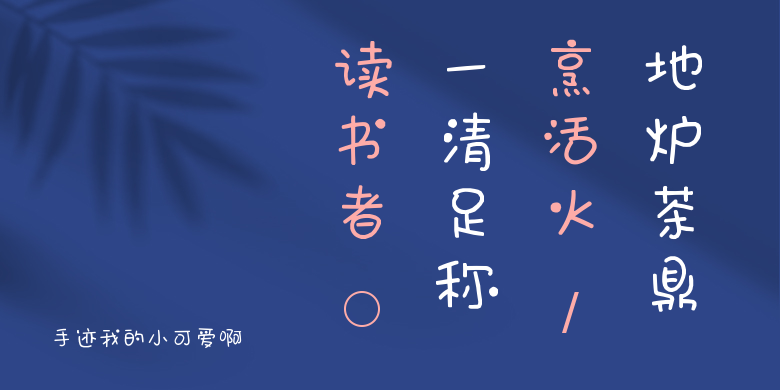
手迹我的小可爱啊
手迹我的小可爱啊,这款字体结构工整、笔画清晰,兼顾美观与易读性,适用于标题、正文、海报、包装、LOGO 等多种场景。字形优雅稳定,风格百搭耐看,适配日常排版与创意设计,让文字呈现更舒适、更具质感。手迹我的小可爱啊一笔一画,皆是细节,以均衡的比例、流畅的线条打造舒适视觉体验,字形端正大气,风格简约现代。无论是商业设计、品牌宣传还是日常排版,都能轻松驾驭,让文字更有格调与力量。手迹我的小可爱啊字体下载。